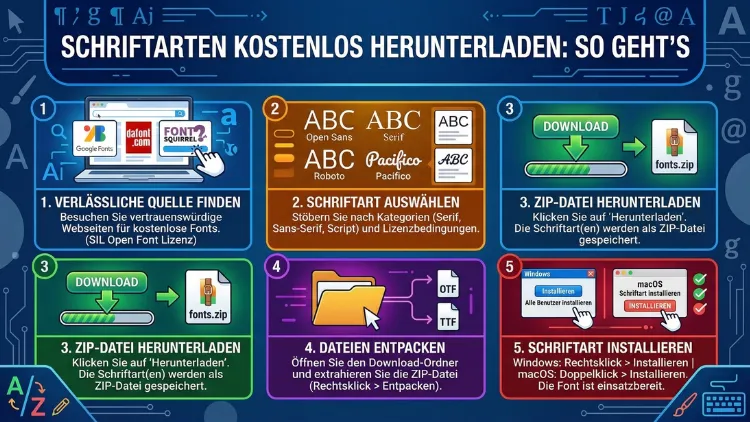
Wie kann ich kostenlose Schriftarten herunterladen?
Erfahren Sie, wie Sie Schriftarten kostenlos herunterladen, sicher installieren und die besten Free-Fonts für Design, Website und Dokumente finden.
Wie kann ich kostenlose Schriftarten herunterladen?
Kostenlose Schriftarten lassen sich heute schnell und legal herunterladen – wenn man weiß, wo man suchen muss. Ob für Windows, Mac oder Linux: Zahlreiche seriöse Plattformen bieten tausende Fonts gratis an, die sich außerdem auch für kommerzielle Projekte nutzen lassen.
Dieser Artikel zeigt Ihnen Schritt für Schritt, welche Quellen wirklich empfehlenswert sind, wie der Download funktioniert und wie Sie Schriftarten korrekt installieren.
Warum kostenlose Schriftarten eine ernsthafte Option sind
Viele Menschen glauben, dass kostenlose Schriftarten minderwertig sind. Das stimmt jedoch längst nicht mehr. Dank offener Lizenzen wie der SIL Open Font License (OFL) und der Apache-Lizenz stellen Designer und Schriftenhersteller weltweit hochwertige Typefaces kostenlos zur Verfügung. Zudem finanzieren Unternehmen wie Google ganze Schriftbibliotheken, die jeder frei nutzen darf.
Deshalb lohnt es sich, die richtigen Quellen zu kennen, bevor man teure Lizenzen kauft. Im Folgenden erfahren Sie, welche Plattformen besonders vertrauenswürdig sind und wie Sie dort gezielt vorgehen.
Die besten Quellen für kostenlose Schriftarten
Google Fonts
Google Fonts ist die bekannteste und meistgenutzte Plattform für kostenlose Schriftarten weltweit. Die Bibliothek umfasst aktuell über 1.500 Schriftfamilien, die alle unter der SIL Open Font License oder der Apache-Lizenz veröffentlicht sind. Das bedeutet: Sie dürfen diese Schriftarten sowohl privat als auch kommerziell verwenden.
Empfehlung: Suchen Sie nach Fonts wie „Inter“, „Roboto“, „Lato“, „Montserrat“ oder „Playfair Display“ – das sind besonders vielseitige und professionelle Schriftfamilien.
Font Squirrel
Font Squirrel ist eine weitere hervorragende Adresse. Die Plattform kuratiert ausschließlich Schriftarten, die ausdrücklich für kommerzielle Nutzung freigegeben sind. Außerdem bietet Font Squirrel einen praktischen Webfont-Generator, mit dem sich Schriften für den Einsatz auf Websites optimieren lassen.
DaFont
DaFont ist besonders für dekorative, kreative und thematische Schriftarten bekannt. Die Auswahl reicht von Gothic und Horror über Handschriften bis hin zu technischen Schriften. Jedoch sollten Sie bei DaFont stets die Lizenzbedingungen des einzelnen Fonts prüfen, da nicht alle Schriftarten automatisch für kommerzielle Zwecke freigegeben sind.
3. Prüfen Sie rechts neben dem Font den Lizenzvermerk – ideal ist „100% Free“ oder „Public Domain“.
4. Klicken Sie auf „Download“.
Fonts und Abstract Fonts
1001fonts.com und abstractfonts.com sind ebenfalls empfehlenswerte Anlaufstellen, vor allem wenn Sie eine breite Auswahl an Handschriften, Retro-Fonts oder speziellen Display-Schriften suchen. Zudem ermöglichen beide Seiten eine Vorschau mit eigenem Text, bevor Sie eine Schriftart herunterladen.
The League of Moveable Type
theleagueofmoveabletype.com ist eine kleinere, aber qualitativ hochwertige Sammlung von Open-Source-Schriftarten. Alle Fonts sind von professionellen Typografen gestaltet und für jegliche Nutzung freigegeben. Besonders empfehlenswert ist hier zum Beispiel „Raleway“ – eine elegante Sans-Serif-Schrift, die sich ideal für Headlines eignet.
Befonts und Freefontspro
befonts.com ist eine neuere Plattform, die regelmäßig frische, professionell gestaltete Schriftarten veröffentlicht. Viele davon sind kostenlos verfügbar, allerdings häufig nur für den privaten Gebrauch. Deshalb sollten Sie auch hier stets den Lizenzvermerk prüfen. freefontspro.com hingegen bietet eine kuratierte Auswahl, bei der kommerzielle Nutzung häufig explizit erlaubt ist. Beide Seiten eignen sich besonders dann, wenn Sie nach aktuellen Schrifttrends Ausschau halten.
Fontshare von Indian Type Foundry
fontshare.com ist eine vergleichsweise neue Plattform der renommierten Indian Type Foundry (ITF). Die Besonderheit: Alle dort angebotenen Schriftarten sind professionell entwickelt und unter einer eigenen freien Lizenz erhältlich, die ausdrücklich auch kommerzielle Nutzung erlaubt. Zudem sind viele Fonts auf Fontshare mehrsprachig und unterstützen zahlreiche Schriftsysteme. Empfehlenswerte Beispiele sind „Satoshi“, „Cabinet Grotesk“ und „Clash Display“ – allesamt moderne, unverwechselbare Schriften, die in professionellen Designs eine starke Wirkung erzielen.
Schriftarten kombinieren: Grundregeln für gelungene Typografie
Das Herunterladen der richtigen Schriftart ist nur der erste Schritt. Ebenso wichtig ist es, Fonts sinnvoll miteinander zu kombinieren, um ein harmonisches und professionelles Erscheinungsbild zu erzielen. Dabei gelten einige bewährte Grundsätze.
Kontrast zwischen Überschrift und Fließtext
Eine der wirkungsvollsten Methoden ist die Kombination einer Serif-Schrift für den Fließtext mit einer Sans-Serif-Schrift für Überschriften – oder umgekehrt. Der Kontrast zwischen den Schriftgattungen erzeugt eine klare visuelle Hierarchie. Zudem ist diese Kombination zeitlos und funktioniert in nahezu jedem Kontext.
Empfehlenswerte Kombinationen (alle kostenlos über Google Fonts):
• Playfair Display (Überschrift) + Source Sans Pro (Fließtext)
• Montserrat (Überschrift) + Merriweather (Fließtext)
• Raleway (Überschrift) + Lora (Fließtext)
• Oswald (Überschrift) + PT Serif (Fließtext)
Schriften aus derselben Familie nutzen
Eine ebenso sichere Methode ist es, verschiedene Gewichte und Stile einer einzigen Schriftfamilie zu kombinieren. Zum Beispiel lässt sich Roboto Light hervorragend für Fließtext und Roboto Bold für Überschriften einsetzen. Dadurch wirkt das Layout konsistent, und außerdem müssen Sie keine Kompatibilitätsprobleme zwischen verschiedenen Fonts befürchten.
Tools zum Testen von Schriftpaaren
Das kostenlose Tool Fontpair.co stellt bewährte Schriftkombinationen übersichtlich dar und zeigt dabei jeweils, wie die Paare in der Praxis aussehen. Zudem bietet Google Fonts auf der Detailseite eines jeden Fonts direkte Empfehlungen für passende Schriftpaare an. Ebenso hilfreich ist Typ.io, das reale Websites als Inspiration für Schriftkombinationen auflistet.
Schriftarten in Design-Programmen einsetzen: Adobe, Canva und Co.
Heruntergeladene Schriftarten lassen sich nicht nur in Office-Programmen, sondern auch in professionellen Design-Anwendungen nutzen. Deshalb lohnt es sich, zu wissen, wie der Einsatz in den gängigsten Programmen funktioniert.
Adobe Photoshop, Illustrator und InDesign
Nachdem Sie eine Schriftart auf Ihrem System installiert haben, steht sie automatisch in allen Adobe-Programmen zur Verfügung. Starten Sie das jeweilige Programm nach der Installation neu, damit die neuen Fonts geladen werden. Alternativ bietet Adobe Fonts (früher Typekit) im Rahmen einer Creative-Cloud-Lizenz tausende weitere Schriften an – diese lassen sich jedoch nur mit aktiver Lizenz nutzen und sind nicht im eigentlichen Sinne „kostenlos herunterladbar“.
Canva
Canva erlaubt in der kostenlosen Version das Hochladen eigener Schriftarten. Gehen Sie dazu folgendermaßen vor:
1. Öffnen Sie Ihr Canva-Konto und navigieren Sie zu „Brand Kit“.
2. Klicken Sie auf „Schriftart hochladen“.
3. Laden Sie Ihre heruntergeladene OTF- oder TTF-Datei hoch.
4. Die Schriftart steht Ihnen anschließend in allen Designs zur Verfügung.
Allerdings ist das Hochladen eigener Fonts in Canva nur mit einem Canva Pro-Konto möglich. In der kostenlosen Version stehen jedoch bereits hunderte Google-Fonts direkt in der Anwendung bereit.
GIMP und Inkscape (Open-Source-Alternativen)
Die kostenlosen Programme GIMP (Bildbearbeitung) und Inkscape (Vektorgrafik) greifen automatisch auf alle systemweit installierten Schriften zu. Deshalb genügt es, den Font wie beschrieben zu installieren, damit er in diesen Programmen unmittelbar nutzbar ist.
LibreOffice und OpenOffice
Auch in LibreOffice Writer, Calc und Impress sowie in OpenOffice erscheinen alle installierten Systemschriften automatisch in der Schriftartauswahl. Ein Programm-Neustart nach der Installation ist dabei in der Regel ausreichend.
Schriftarten sicher herunterladen: Worauf Sie achten sollten
Leider nutzen manche unseriösen Seiten die Popularität kostenloser Schriftarten aus, um Schadsoftware zu verbreiten. Deshalb ist es wichtig, einige Sicherheitshinweise zu beachten.
Achten Sie auf diese Warnsignale:
• Die Downloadseite fordert Sie auf, zusätzliche Software oder „Download-Manager“ zu installieren.
• Die Schriftartdatei hat eine ungewöhnliche Endung wie .exe, .zip mit Passwort oder .js.
• Die Seite zeigt übermäßig viele Pop-ups und Weiterleitungen.
• Der Dateiname der heruntergeladenen Datei entspricht nicht dem Fontnamen.
Empfohlene Vorgehensweisen für sicheres Herunterladen:
• Nutzen Sie ausschließlich die bereits genannten vertrauenswürdigen Plattformen.
• Prüfen Sie heruntergeladene Dateien mit einem aktuellen Antivirenprogramm, zum Beispiel Windows Defender (kostenlos, bereits in Windows integriert) oder Malwarebytes Free.
• Laden Sie Fonts niemals von Tauschbörsen, Torrent-Seiten oder nicht verifizierten Dropbox-/Google-Drive-Links herunter.
• Wenn Sie unsicher sind, ob eine Schriftart sicher ist, öffnen Sie zunächst nur die Vorschauansicht im Windows Explorer (Einzelklick auf die TTF-Datei), bevor Sie sie installieren.
Schriftarten finden, wenn man nur das Aussehen kennt
Oft sucht man nach einer Schrift, die man irgendwo gesehen hat, deren Namen man aber nicht kennt. Deshalb gibt es dafür spezialisierte Tools:
WhatTheFont von MyFonts
WhatTheFont (whatthefont.com) ist ein KI-gestützter Schrifterkennungsdienst. Laden Sie einfach ein Bild oder Screenshot hoch, auf dem der gewünschte Text zu sehen ist, und das Tool schlägt die am besten passenden Schriftarten vor. Zudem zeigt es kostenlose Alternativen an, wenn die erkannte Schrift kostenpflichtig ist.
Font Squirrel Matcherator
Der Font Squirrel Matcherator (fontsquirrel.com/matcherator) funktioniert ähnlich wie WhatTheFont, konzentriert sich jedoch ausschließlich auf kostenlose Schriftarten. Er ist deshalb besonders nützlich, wenn Sie nach einer freien Alternative zu einer bekannten, kostenpflichtigen Schrift suchen.
Google Lens
Google Lens auf dem Smartphone erkennt ebenfalls Schriftarten in Fotos. Halten Sie die Kamera einfach auf den betreffenden Text, und Google zeigt Ihnen häufig direkt die verwendete Schrift oder eine sehr ähnliche Alternative an.
Nachdem Sie eine Schriftart heruntergeladen und die ZIP-Datei entpackt haben, sind nur wenige Klicks nötig, um die Schrift auf Ihrem Windows-System zu installieren.
Methode 1 – Direktinstallation per Rechtsklick:
1. Navigieren Sie zu der heruntergeladenen TTF- oder OTF-Datei.
2. Klicken Sie mit der rechten Maustaste auf die Datei.
3. Wählen Sie „Installieren“ (für den aktuellen Benutzer) oder „Für alle Benutzer installieren“.
4. Die Schriftart ist sofort in allen kompatiblen Programmen wie Word, Photoshop oder Canva verfügbar.
Methode 2 – Über die Schriftarteneinstellungen:
1. Öffnen Sie die Windows-Einstellungen (Windows-Taste + I).
2. Navigieren Sie zu „Personalisierung“ → „Schriftarten“.
3. Ziehen Sie die TTF- oder OTF-Datei per Drag-and-drop in das Fenster.
4. Windows installiert die Schriftart automatisch.
Tipp: Wenn Sie viele Fonts gleichzeitig installieren möchten, empfiehlt sich das kostenlose Tool NexusFont oder FontBase. Damit lassen sich außerdem Schriftarten organisieren, deaktivieren und in Gruppen einteilen, ohne sie zu deinstallieren.
Schriftarten auf dem Mac installieren
Auch auf einem Mac ist die Installation unkompliziert. Zudem bietet macOS eine eigene Verwaltungsoberfläche für Schriften.
Schritt-für-Schritt-Anleitung:
1. Laden Sie die gewünschte Schriftart herunter und entpacken Sie die ZIP-Datei.
2. Doppelklicken Sie auf die TTF- oder OTF-Datei.
3. Es öffnet sich das Schriftarten-Vorschaufenster mit einem Button „Schrift installieren“.
4. Klicken Sie darauf – die Schrift wird sofort systemweit verfügbar.
Alternativ können Sie die Datei direkt in die App „Schriftenbuch“ (Font Book) ziehen, die Apple vorinstalliert hat. Dort lassen sich zudem Schriften aktivieren, deaktivieren und in Sammlungen organisieren.
Schriftarten unter Linux installieren
Unter Linux ist die Installation ebenfalls einfach, unterscheidet sich jedoch je nach Distribution leicht. Deshalb zeigen wir Ihnen die universelle Methode:
Für einzelne Benutzer:
1. Erstellen Sie im Heimverzeichnis den Ordner ~/.fonts (falls er noch nicht existiert).
2. Kopieren Sie die TTF- oder OTF-Datei in diesen Ordner.
3. Führen Sie im Terminal den Befehl fc-cache -fv aus, um den Schriften-Cache zu aktualisieren.
Systemweit für alle Benutzer:
1. Kopieren Sie die Schriftartdateien nach /usr/share/fonts/.
2. Aktualisieren Sie den Cache ebenfalls mit fc-cache -fv.
Unter Ubuntu lassen sich außerdem viele gängige Schriftartenpakete direkt über den Paketmanager installieren – zum Beispiel mit dem Befehl sudo apt install fonts-open-sans.
Das richtige Dateiformat wählen: TTF, OTF, WOFF und mehr
Nicht alle Schriftartformate eignen sich für jeden Einsatzzweck. Deshalb ist es wichtig, den Unterschied zu kennen:
• TTF (TrueType Font): Das älteste und verbreitetste Format. Funktioniert zuverlässig unter Windows, Mac und Linux. Außerdem wird es von den meisten Programmen unterstützt.
• OTF (OpenType Font): Das modernere Format. Es unterstützt erweiterte typografische Funktionen wie Ligaturen, alternative Zeichen (Glyphen) und mehrsprachige Zeichensätze. Deshalb ist OTF für professionelle Anwendungen meist die bessere Wahl.
• WOFF/WOFF2 (Web Open Font Format): Speziell für den Einsatz auf Websites optimiert. Diese Formate sind komprimiert und laden dadurch schneller. Allerdings lassen sie sich nicht direkt auf einem Desktop-System installieren.
• Variable Fonts: Eine neuere Entwicklung, bei der eine einzige Datei verschiedene Gewichte, Breiten und Stile enthält. Google Fonts bietet zunehmend Variable Fonts an, die außerdem Dateigrößen reduzieren.
Empfehlung: Für den Desktop-Einsatz wählen Sie stets OTF, sofern verfügbar. Für Websites nutzen Sie WOFF2 für maximale Performance.
Schriftarten auf Websites einbinden – die wichtigsten Methoden
Wenn Sie eine heruntergeladene Schriftart auf einer eigenen Website nutzen möchten, gibt es zwei empfohlene Vorgehensweisen:
Methode 1: Google Fonts per CSS-Import einbinden
Dies ist die einfachste und schnellste Methode, wenn Sie eine Google-Schriftart verwenden möchten:
1. Gehen Sie auf fonts.google.com und wählen Sie Ihren Font.
2. Klicken Sie auf „Get embed code“.
3. Kopieren Sie den @import-Code und fügen Sie ihn am Anfang Ihrer CSS-Datei ein.
4. Wenden Sie die Schrift über font-family in Ihrem CSS an.
Methode 2: Self-Hosting mit @font-face
Für mehr Kontrolle und bessere Ladezeiten empfiehlt sich das Self-Hosting:
1. Laden Sie die Schriftart herunter und konvertieren Sie sie bei Bedarf mit dem Font Squirrel Webfont Generator in WOFF2.
2. Laden Sie die Dateien auf Ihren Webserver.
3. Binden Sie die Schrift in Ihrer CSS-Datei ein:
@font-face {
font-family: 'MeineSchrift';
src: url('fonts/meineschrift.woff2') format('woff2'),
url('fonts/meineschrift.woff') format('woff');
font-weight: normal;
font-style: normal;
font-display: swap;
}
Zudem sollten Sie stets font-display: swap verwenden, um Ladeprobleme zu vermeiden und die Core Web Vitals Ihrer Website zu verbessern.
Lizenzen verstehen: Was darf man mit kostenlosen Fonts wirklich?
Kostenlos bedeutet nicht immer unbegrenzt nutzbar. Deshalb sollten Sie die Lizenz jedes Fonts prüfen, bevor Sie ihn für kommerzielle Projekte einsetzen.
Die häufigsten Lizenztypen bei kostenlosen Schriftarten sind:
• SIL Open Font License (OFL): Erlaubt private und kommerzielle Nutzung, auch in eingebetteten Dokumenten und auf Websites. Einzige Bedingung: Der Fontname darf beim Weiterverkauf nicht geändert werden.
• Apache 2.0: Ähnlich wie OFL, ebenfalls für kommerzielle Projekte geeignet.
• CC BY (Creative Commons Attribution): Erlaubt Nutzung und Änderung, jedoch muss der Urheber genannt werden.
• Freeware – nur für privaten Gebrauch: Diese Fonts dürfen außerdem nicht kommerziell genutzt werden. Bei DaFont ist dieser Vermerk häufig zu finden.
• Public Domain/CC0: Vollständig frei – keine Einschränkungen, keine Pflichtangaben.
Empfehlung: Für kommerzielle Projekte nutzen Sie ausschließlich Schriftarten unter OFL, Apache oder CC0. Google Fonts und Font Squirrel erfüllen diese Anforderung zuverlässig.
Empfohlene Vorgehensweisen beim Umgang mit Schriftartsammlungen
Wer regelmäßig mit Schriftarten arbeitet, sammelt schnell hunderte Fonts an. Deshalb lohnt es sich, diese von Anfang an sauber zu verwalten:
• FontBase (kostenlos, für Windows/Mac/Linux): Ermöglicht es, Fonts zu organisieren, in Sammlungen einzuteilen und einzelne Schriften temporär zu deaktivieren, ohne sie zu löschen. Zudem synchronisiert FontBase automatisch mit Google Fonts.
• NexusFont (kostenlos, Windows): Leichtgewichtige Alternative mit Vorschaufunktion und Schnellsuche.
• RightFont (Mac, kostenpflichtig): Professionelles Font-Management für Designer, jedoch mit mehr Funktionen als die kostenlosen Alternativen.
Außerdem empfiehlt es sich, einen separaten Ordner für lizenzierte Fonts anzulegen und die jeweilige Lizenzdatei (meist eine TXT- oder PDF-Datei, die beim Download mitgeliefert wird) gemeinsam mit den Font-Dateien zu speichern. So vermeiden Sie spätere Unsicherheiten bei kommerziellen Projekten.
Typische Fehler beim Herunterladen und Installieren vermeiden
Viele Nutzer machen beim Umgang mit Schriftarten vermeidbare Fehler. Deshalb hier die häufigsten Probleme und deren Lösung:
Problem 1: Die Schrift erscheint nicht in Word oder Photoshop.
Lösung: Starten Sie das Programm nach der Installation neu. Zudem kann es helfen, Windows oder macOS einmal neu zu starten, damit alle Programme den aktualisierten Schriften-Cache laden.
Problem 2: Die ZIP-Datei enthält viele einzelne Gewichte.
Lösung: Installieren Sie alle enthaltenen Dateien (Light, Regular, Bold, Italic usw.), um die vollständige Schriftfamilie zu erhalten. Sonst fehlen z. B. fette oder kursive Varianten.
Problem 3: Sonderzeichen oder Umlaute werden falsch dargestellt.
Lösung: Prüfen Sie, ob der Font einen vollständigen Latin Extended-Zeichensatz enthält. Viele dekorative Fonts unterstützen lediglich das englische Alphabet. Wählen Sie in diesem Fall einen Font mit umfangreicherem Zeichensatz.
Problem 4: Der Font wird als beschädigte Datei angezeigt.
Lösung: Laden Sie die Datei erneut herunter oder nutzen Sie eine alternative Quelle. Außerdem kann ein Antivirusprogramm Font-Dateien fälschlicherweise blockieren – prüfen Sie ggf. die Quarantäneliste.
Schriftarten für spezifische Einsatzbereiche: Empfehlungen
Je nach Anwendungsfall eignen sich unterschiedliche Schriftarten. Hier sind gezielte Empfehlungen für häufige Einsatzbereiche:
Für Präsentationen (PowerPoint, Keynote):
Empfehlenswert sind Montserrat (Sans Serif, modern), Merriweather (Serif, elegant) und Source Sans Pro (klar, gut lesbar). Alle drei sind über Google Fonts kostenlos verfügbar.
Für Logos und Branding:
Raleway, Josefin Sans und Playfair Display bieten einen hohen Wiedererkennungswert und sind für kommerzielle Nutzung freigegeben.
Für lange Texte und Fließtext:
Hier empfiehlt sich Lora, EB Garamond oder Libre Baskerville – alle gut lesbar und auf Bildschirm wie im Druck geeignet.
Für Kreativprojekte und Handschriften:
Pacifico, Dancing Script oder Caveat (alle bei Google Fonts) verleihen Projekten eine persönliche Note. Jedoch sollten Sie diese Schriften sparsam einsetzen, da sie bei langen Texten die Lesbarkeit einschränken.
FAQ: Häufige Fragen zum Herunterladen kostenloser Schriftarten
Sind kostenlose Schriftarten wirklich legal nutzbar?
Ja, sofern Sie die richtige Lizenz wählen. Schriftarten unter der SIL Open Font License oder der Apache-Lizenz sind sowohl für private als auch für kommerzielle Zwecke vollständig legal nutzbar. Deshalb sollten Sie stets den Lizenzvermerk auf der jeweiligen Downloadseite prüfen.
Kann ich kostenlose Fonts in kommerziellen Projekten wie Logos oder Flyern verwenden?
Das hängt von der Lizenz ab. Fonts unter OFL und Apache erlauben kommerzielle Nutzung ausdrücklich. Jedoch sind viele Fonts bei DaFont nur für den privaten Gebrauch freigegeben. Google Fonts und Font Squirrel sind hingegen für kommerzielle Projekte zuverlässig geeignet.
Wie viele Schriftarten kann ich gleichzeitig installieren?
Es gibt keine offizielle Obergrenze, jedoch verlangsamen zu viele installierte Fonts manche Programme. Deshalb empfiehlt es sich, nicht benötigte Schriften zu deaktivieren – zum Beispiel mit FontBase – anstatt sie dauerhaft zu installieren.
Warum zeigt Word meine neu installierte Schrift nicht an?
Meistens liegt das daran, dass Word vor der Installation geöffnet war. Starten Sie Word nach der Installation neu. Zudem kann ein Windows-Neustart helfen, wenn das Problem anhält.
Was ist der Unterschied zwischen TTF und OTF?
TTF ist das ältere Format, das auf nahezu allen Systemen läuft. OTF ist hingegen das modernere Format mit mehr typografischen Funktionen wie Ligaturen und Glyphen. Für professionelle Anwendungen empfiehlt sich OTF, sofern es verfügbar ist.
Kann ich Schriftarten aus dem Internet auf meinem Smartphone nutzen?
Unter Android können Apps wie iFont oder FontFix Schriftarten systemweit installieren, jedoch ist dafür oft Root-Zugriff nötig. Auf dem iPhone/iPad erlaubt iOS ab Version 13 die Installation von Schriften über spezielle Apps wie AnyFont, die im App Store verfügbar sind.
Wo finde ich kostenlose Schriftarten mit deutschen Sonderzeichen?
Auf Google Fonts und Font Squirrel lassen sich Fonts nach unterstützten Zeichensätzen filtern. Wählen Sie unter Google Fonts den Filter „Language → Latin Extended“ oder „Language → German“, um nur Schriften mit vollständigem deutschsprachigem Zeichensatz anzuzeigen.
Sind Schriftarten von dubiosen Download-Seiten sicher?
Nein, von unbekannten Quellen sollten Sie grundsätzlich keine Fonts herunterladen. Manipulierte TTF-/OTF-Dateien können Schadcode enthalten. Laden Sie Schriftarten deshalb ausschließlich von vertrauenswürdigen Plattformen wie Google Fonts, Font Squirrel, DaFont oder 1001 Fonts herunter.
Kann ich heruntergeladene Schriftarten weitergeben oder in PDFs einbetten?
Das ist bei OFL-lizenzierten Fonts erlaubt. Zudem dürfen Fonts in PDFs, E-Books oder andere Dokumente eingebettet werden, solange die Lizenzbedingungen dies gestatten. Prüfen Sie hierzu die jeweilige Lizenzdatei.
Wie finde ich heraus, welche Schriftart auf einer Website verwendet wird?
Mit dem kostenlosen Browser-Plugin WhatFont (für Chrome und Firefox) erkennen Sie per Mauszeiger sofort, welche Schrift auf einer Seite eingesetzt wird. Ebenso zeigt das Browser-Entwicklerwerkzeug (F12) unter „Computed Styles“ die verwendeten Schriftfamilien an.
Fazit
Kostenlose Schriftarten sind heute qualitativ hochwertig, legal nutzbar und leicht zu finden. Google Fonts und Font Squirrel sind die empfohlenen Anlaufstellen für zuverlässige, kommerziell einsetzbare Fonts.